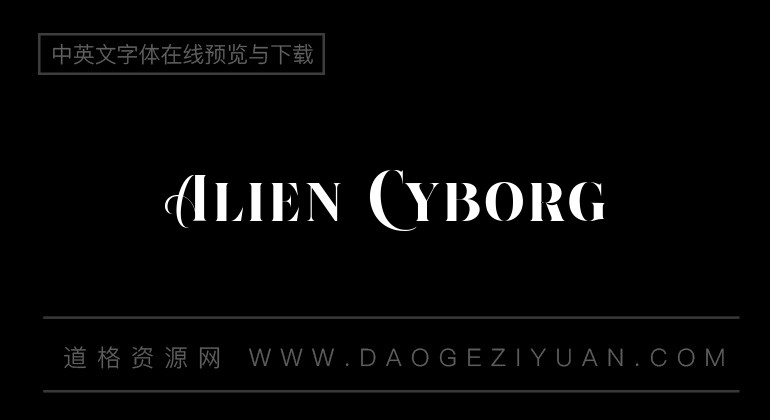
Alien Cyborg 字体是由 Fontalicious 公司推出的一款抽象风格的英文字体,它的字体设计灵感来自外星机器人的形象,充满了未来感。这款字体采用了细节丰富的线条设计,具有非常独特的外观,可以用来装饰多种不同的媒体,包括海报、网站、电影片头等。它可以带来一种超现实的感觉,能够让用户产生强烈的视觉冲击,激发他们的想象力,为他们的创作提供新的灵感。内容介绍
Alien Cyborg是一款非常不错的手写艺术字体,具有很好的视觉感,适合于文化类的宣传设计、商业类品牌的广告和产品包装设计以及个性化文字排版等较多场景。